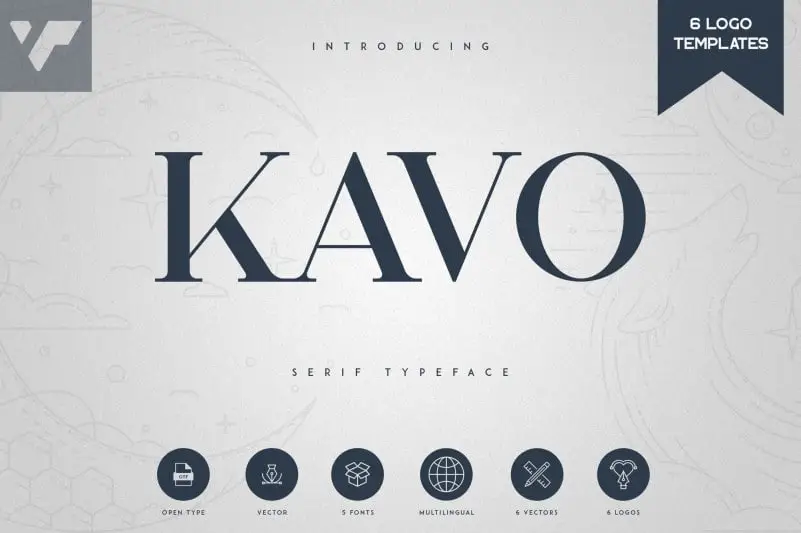
Kavo Serif Typeface – 5 Weights + 6 Logo Templates – Download Grátis
Kavo Serif Typeface é uma elegante tipografia séria com cinco pesos, seis designs vectoriais incríveis, seis moldes para logomarcas e suporte multilinguístico. Com seu design limpo e moderno, esta fonte é versátil e perfeita tanto para projetos grandes quanto pequenos. Se você busca uma fonte séria que possa se adequar a diversos usos, Kavo Serif Typeface é uma excelente escolha. Suas várias opções de peso permitem ajustes finos para diferentes contextos de uso, enquanto as seis marcas vectoriais fornecidas oferecem uma variedade imensa e personalizável, desde designs minimalistas até mais elaborados. Com suporte a vários idiomas, você pode criar projetos multiculturais sem qualquer problema. Seja para aplicativos digitais ou impressão em grandes quantidades, Kavo Serif Typeface é uma opção perfeita que se destaca por sua simplicidade e elegância.